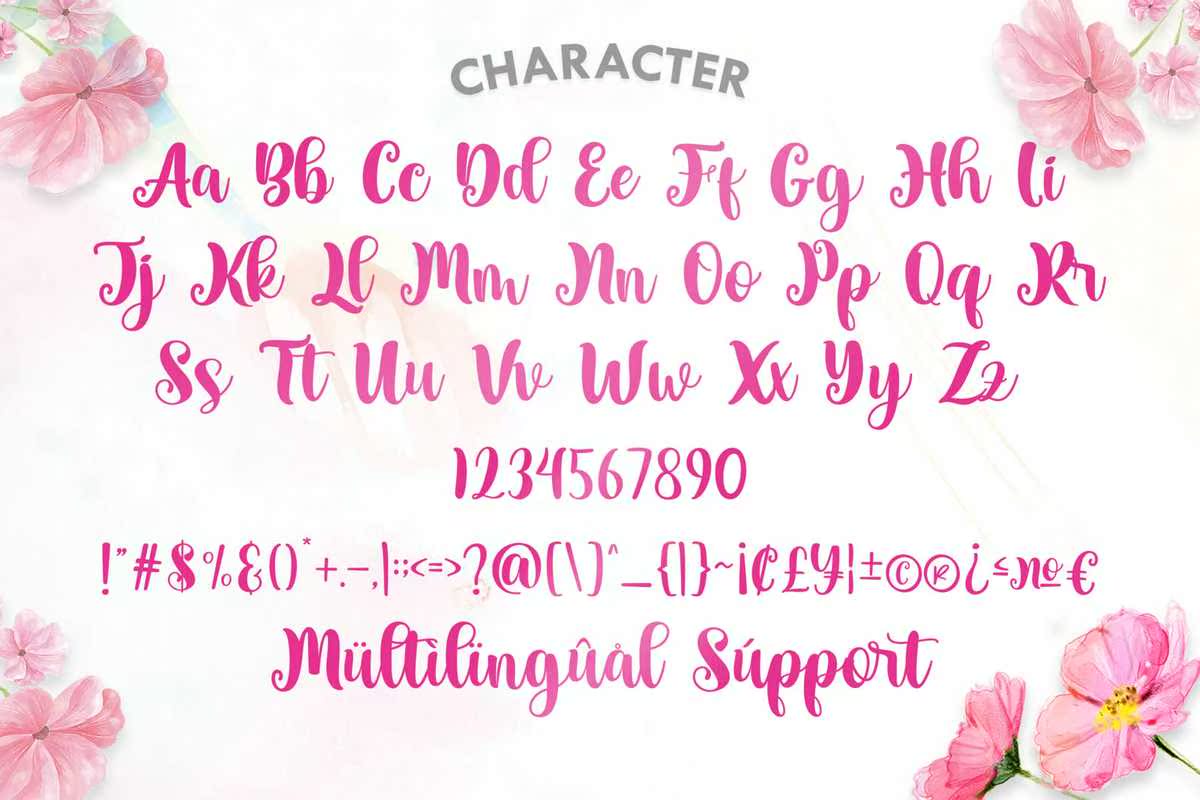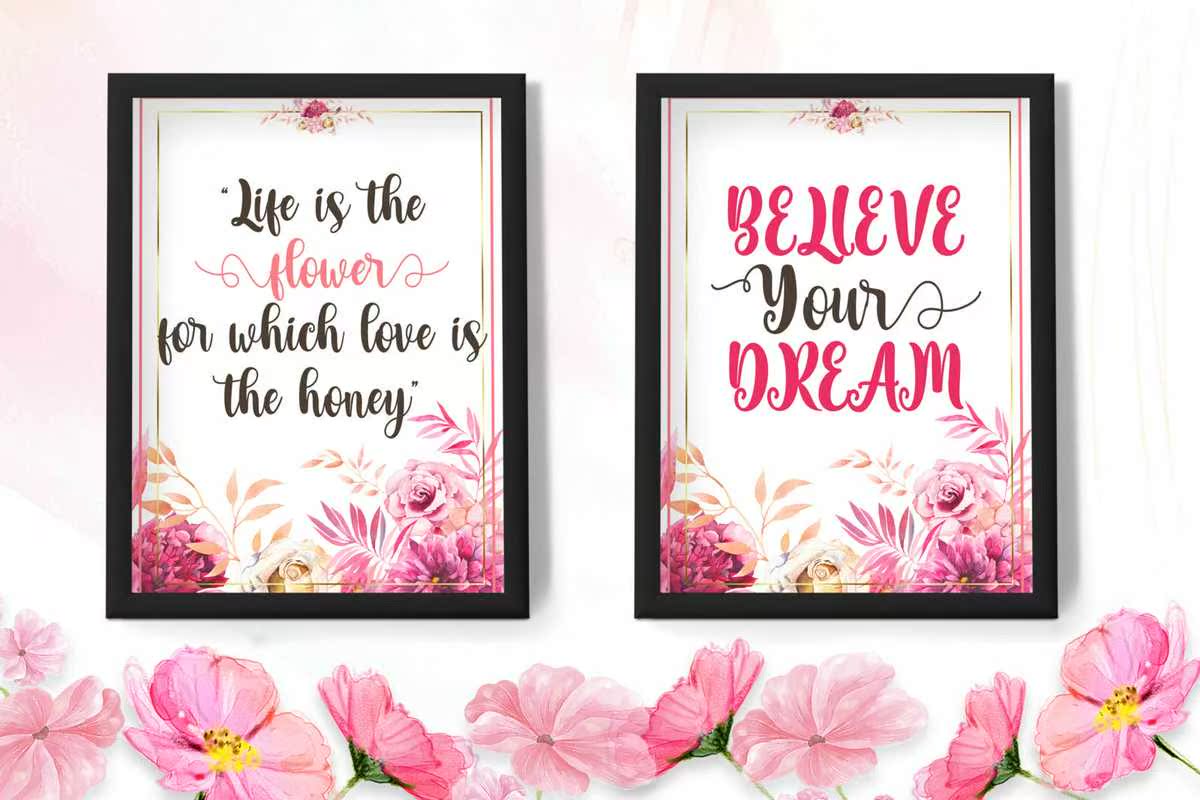
这是一款适用于情人节各种基本特征、细线、经典和优雅线条的休闲拼图字体。可用于各种用途。如图案、签名、徽标、婚礼庆典、t恤、信头、铭牌、标签、新闻、海报、徽章等。这是一款适用于情人节各种基本特征、细线、,经典优雅的线条。可用于各种用途。如图案、签名、徽标、婚礼庆典、t恤、信头、铭牌、标签、新闻、海报、徽章等。